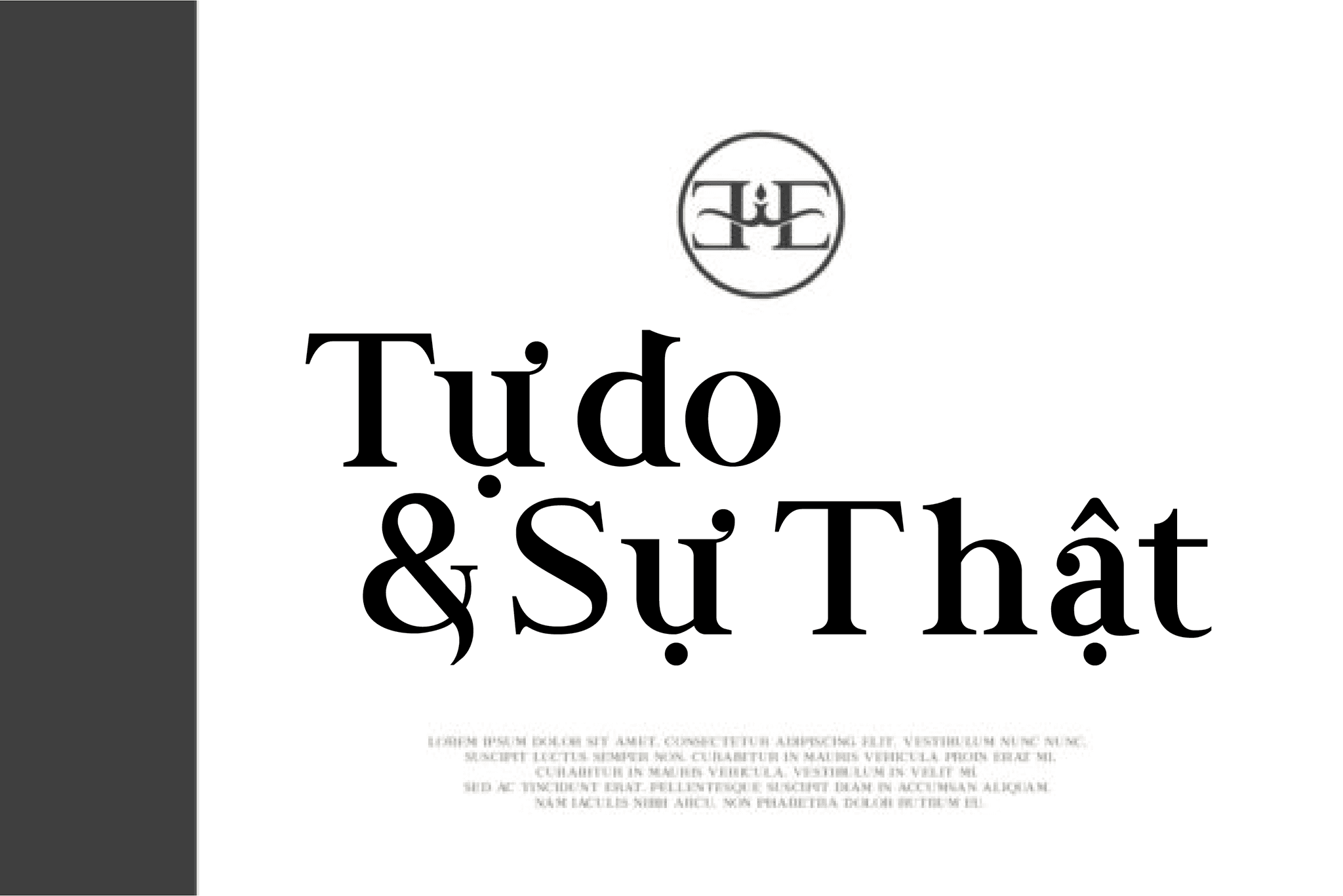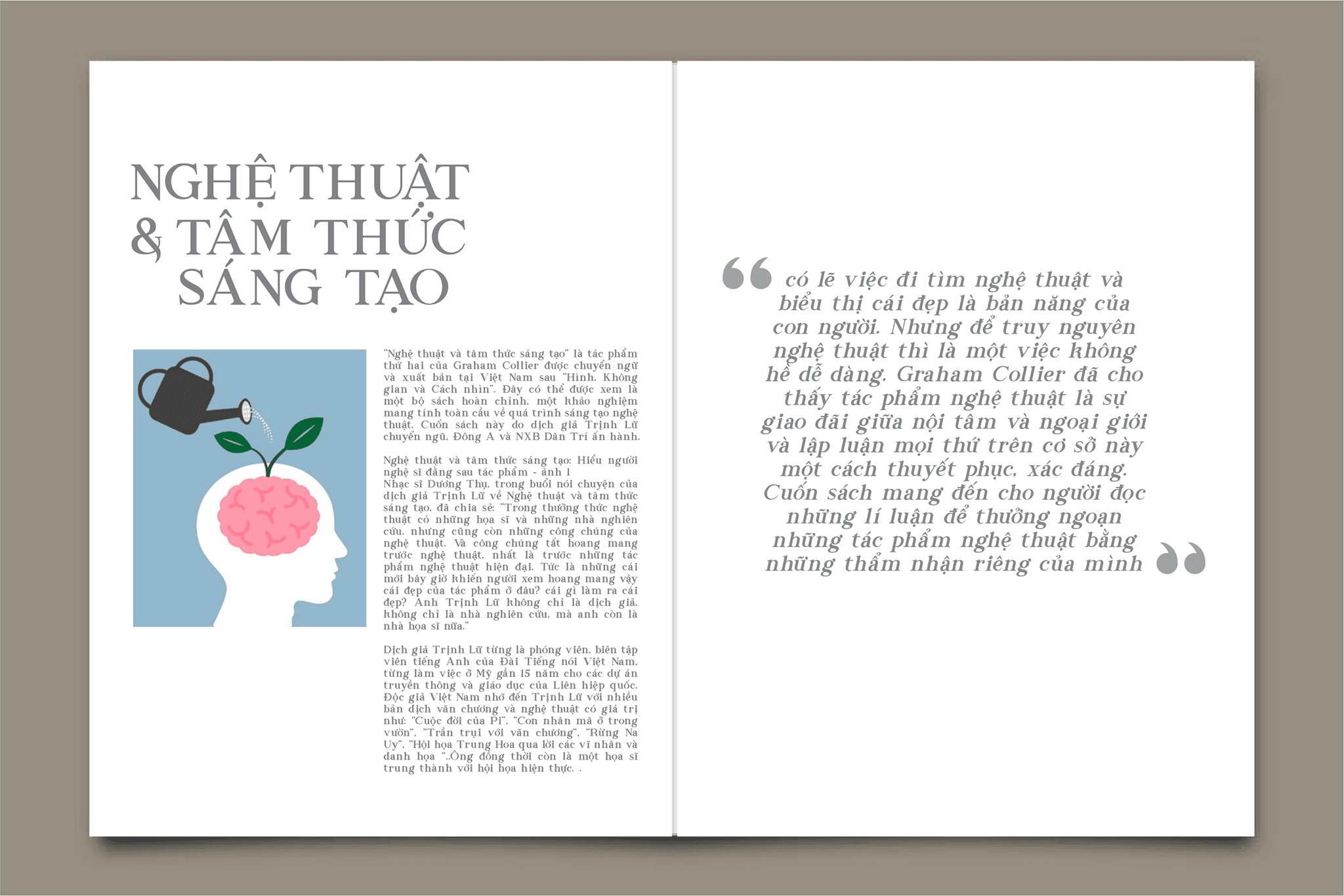
Font Emphatic Việt Hóa. Emphatic là một phông chữ serif đơn giản, thanh lịch và rất đẹp. Nó có thể dễ dàng được kết hợp với một tập hợp lớn các dự án, vì vậy hãy thêm nó vào ý tưởng sáng tạo của bạn và chú ý cách nó làm cho chúng nổi bật!
Font Emphatic Việt Hóa gồm 2 kiểu thường và nghiêng. Một font serif đơn giản nhưng có thể áp dụng vào nhiều thiết kế khác nhau.